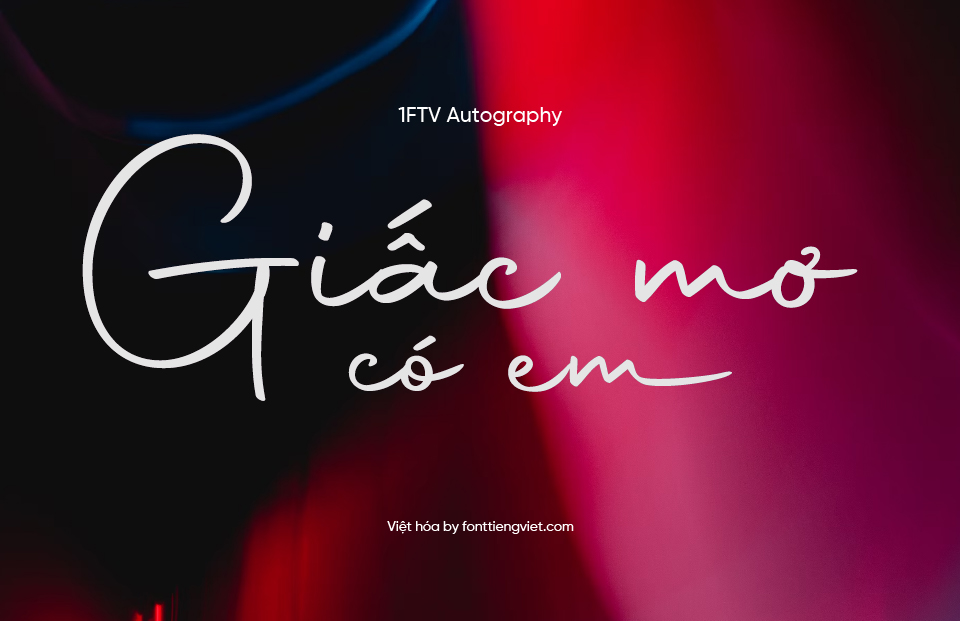
Font Việt hóa 1FTV Autography
Tải Ngay Font Việt hóa 1FTV Autography – Nét Chữ Ký Nghệ Thuật Cho Thiết Kế
Trong thế giới thiết kế đồ họa hiện đại, việc tìm kiếm một bộ Font Việt hóa 1FTV Autography chất lượng là ưu tiên hàng đầu của các bạn trẻ và thầy cô giáo. Đây là mẫu Font Miễn Phí mang phong cách chữ viết tay mềm mại, giúp bài thuyết trình hay thiệp chúc mừng trở nên sinh động hơn. Với các đường nét thanh mảnh và uyển chuyển, bộ phông này mô phỏng hoàn hảo nét chữ ký tự nhiên, tạo cảm giác gần gũi nhưng không kém phần chuyên nghiệp cho mọi tác phẩm sáng tạo tại trường học.
Ưu điểm nổi bật của Font Việt hóa 1FTV Autography trong học tập
Lý do khiến Font Việt hóa 1FTV Autography được yêu thích chính là sự tinh tế trong từng nét chữ. Phông chữ này đã được tối ưu hóa bảng mã tiếng Việt, giúp người dùng không còn lo lắng về lỗi hiển thị dấu câu hay các ký tự đặc biệt. Ứng dụng của nó rất đa dạng, từ việc trang trí bìa tiểu luận, làm thiệp mời sự kiện trường học cho đến việc thiết kế các đoạn trích dẫn ý nghĩa trên mạng xã hội.
Khả năng ứng dụng linh hoạt trên nhiều thiết bị
Để tận dụng tối đa vẻ đẹp của Font Việt hóa 1FTV Autography, bạn nên kết hợp nó với các phông chữ không chân (sans-serif) đơn giản để tạo sự tương phản. Khi trình bày, hãy chú ý đến khoảng cách dòng và kích thước chữ để đảm bảo nội dung luôn dễ đọc và thu hút ánh nhìn. Đây là lựa chọn tuyệt vời để làm nổi bật tên riêng hoặc các tiêu đề quan trọng trong dự án của bạn. Hãy truy cập Font Miễn Phí, Font Việt Hóa, Font Việt hóa 1FTV Autography để sở hữu ngay bộ sưu tập đẳng cấp này cho công việc học tập hằng ngày.